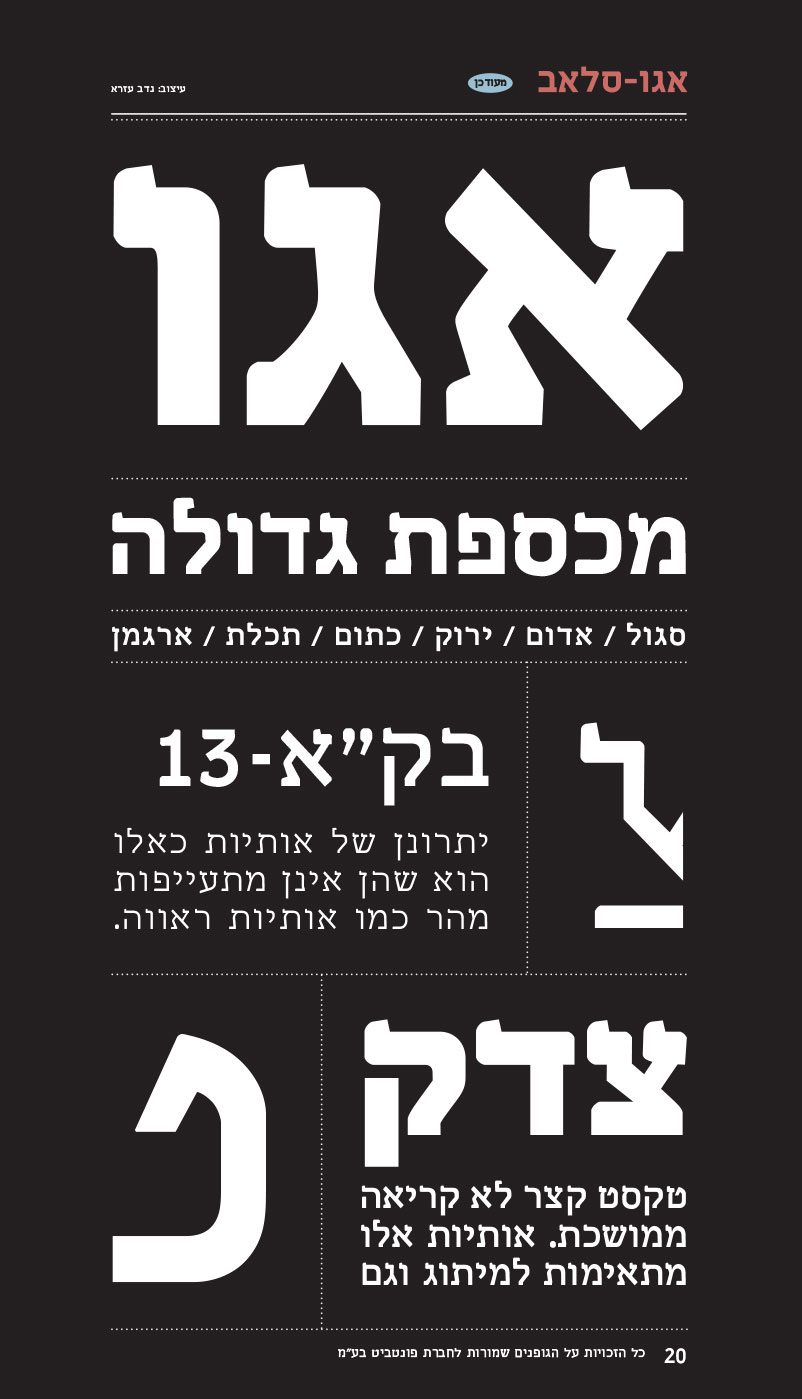
אגו סלאב
אגו סלאב / Fb EgoSlabSerif
• שם הגופן:אגו סלאב
• מעצב הגופן:נדב עזרא
• סגנון:סריף
• קטגוריה: עברית טקסט ספר ראווה
• מאפיינים: קל רגיל כבד שחור
• תכונות: אוונגרדי מרובע נוסטלגי קלאסי קשיח
סיפור הגופן:
אגואיסט, אגוצנטרי... אולי ככה בעצם הוצאנו ל״אגו״ שם רע? אבל בעיני אגו אינו טוב או רע, אלא בסך הכל מתפקד כשומר הסף של ייחודיותנו. כאשר האגו מותאם למידות שלנו אז מתקיים איזון מופלא. בחרתי בשם ״אגו״ לטיפוס אות זה, מפני שיותר מהכל הוא מאופיין בהדגשת הייחודיות המתקיימת בכל אחת מאותיות האלפבית. אבל האתגר האמיתי הוא בשמירה על איזון המידות, אשר מוכתב על ידי אחדות המרכיבים - חוקיות כמערכת המתגלה דרך הרמוניה, גמישות וריקוד. זהו מבחינתי טיפוס אות ראשון מסוגו שמביא את האלפבית העברי בצורתו המקורית כביטוי גרפי, סלאב סריפי(סריף הנאמן לעוביו של קו האות), המוכר לנו מהעולם של אות הדפוס הלטינית.